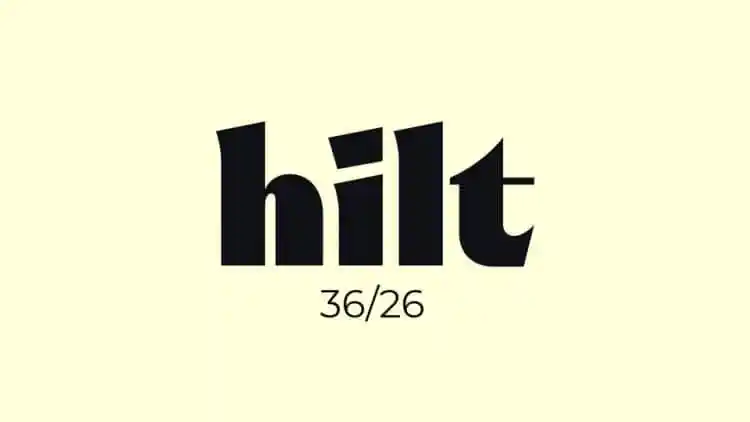
Hilt Sans Serif Font – Fonte Grátis
Hilt Sans Serif Font
A Hilt Sans Serif Font é uma tipografia sans serif moderna inspirada nos traços finos e agudos dos desenhos de pontos de agulha. Esta fonte atinge a perfeição com seus caracteres fortes, especialmente no tamanho mais escura, o que a torna uma escolha ideal para uso em exposições e displays de sinalização. Ela se destaca pela sua elegância limpa e pela capacidade de transmitir uma mensagem clara e moderna sem comprometer a seriedade necessária para ambientes corporativos ou comerciais. Essencialmente, Hilt Sans Serif é perfeita tanto para gráficos digitais quanto para design tradicional, oferecendo uma opção versátil e contemporânea que combina bem com qualquer estilo de projetos visuais.